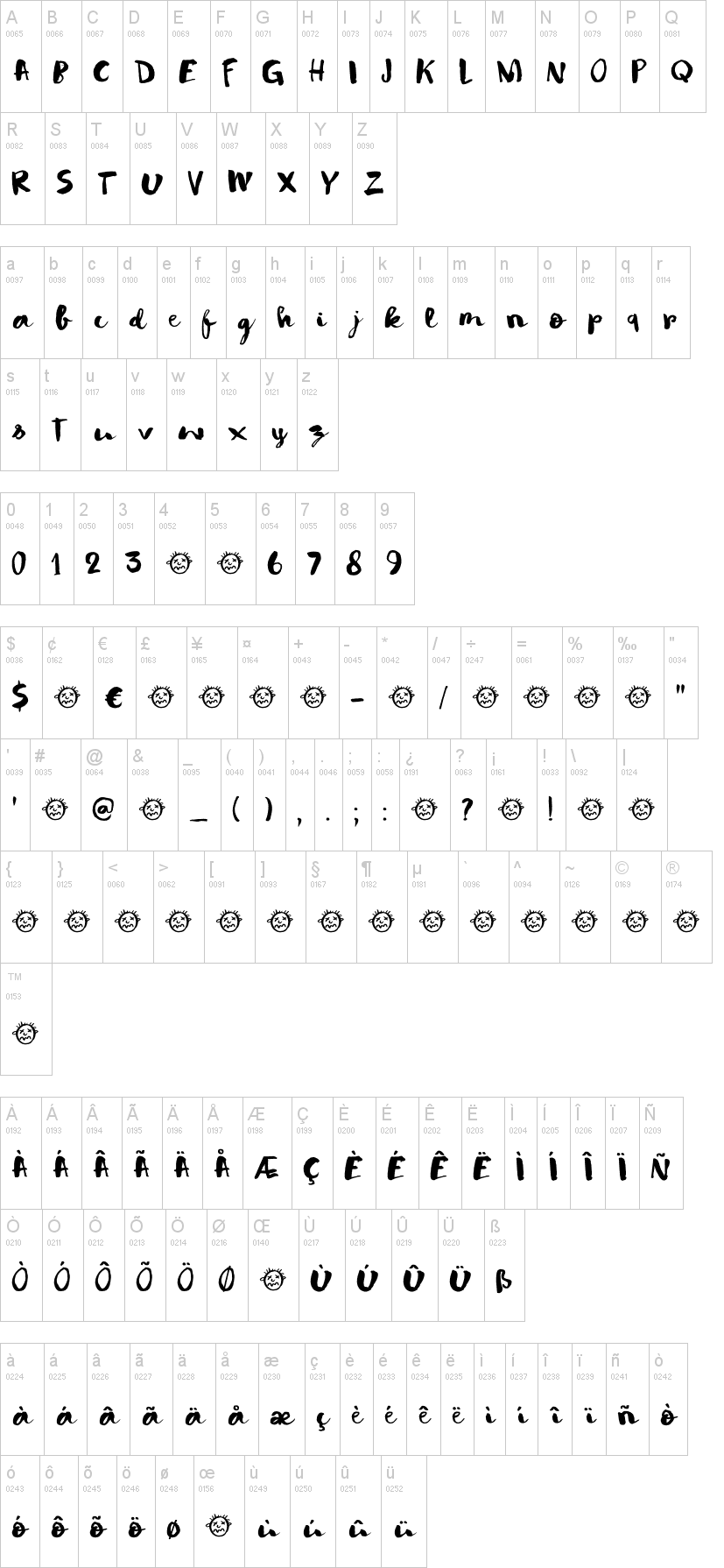
Symptomatic
Symptomatic 是一款由 Fontfabric 创建的现代字体,它具有简洁、清新、灵活的外观,为设计师提供了一种新颖的方式来创建品牌标志、标题、报纸标题、海报、网页等等。Symptomatic 字体采用了新的设计元素,如曲线线条、粗细变化、细节和复杂的字母结构,以及独特的符号,使得它的外观更加灵活,可以适应不同的文本类型。它的字体家族还包括多种字体样式,如常规、粗体、斜体和圆体,以及多种字号,从小到大,可以满足不同的设计需求。
Symptomatic是一款非常不错的手写艺术字体,具有很好的视觉感,适合于文化类的宣传设计、商业类品牌的广告和产品包装设计以及个性化文字排版等较多场景。
Symptomatic字符映射图